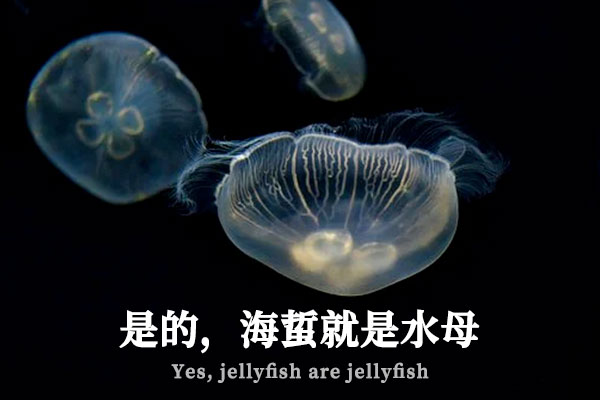
极影毁片辉宋
极影毁片辉宋(KTXP-Kaguya-Serif-Bold)是由中国大陆的九阳飞羽对思源宋体Bold进行修改而成的字体。该字体在原始字形的基础上进行了纵向加粗的改造,从而使字体内横向的笔画变得更加粗壮。
这款字体支持简体中文、繁体中文以及日语字符的显示。在字幕制作过程中,有时会需要使用到类似标题宋的字体。然而,与国内某知名字体设计品牌的中宋体相比,思源宋体家族的横向线条显得过于纤细,导致难以看清。因此,九阳飞羽通过程序将思源宋体的横向线条加粗,从而使其在字幕显示中更加清晰易分辨。
极影毁片辉宋效果预览